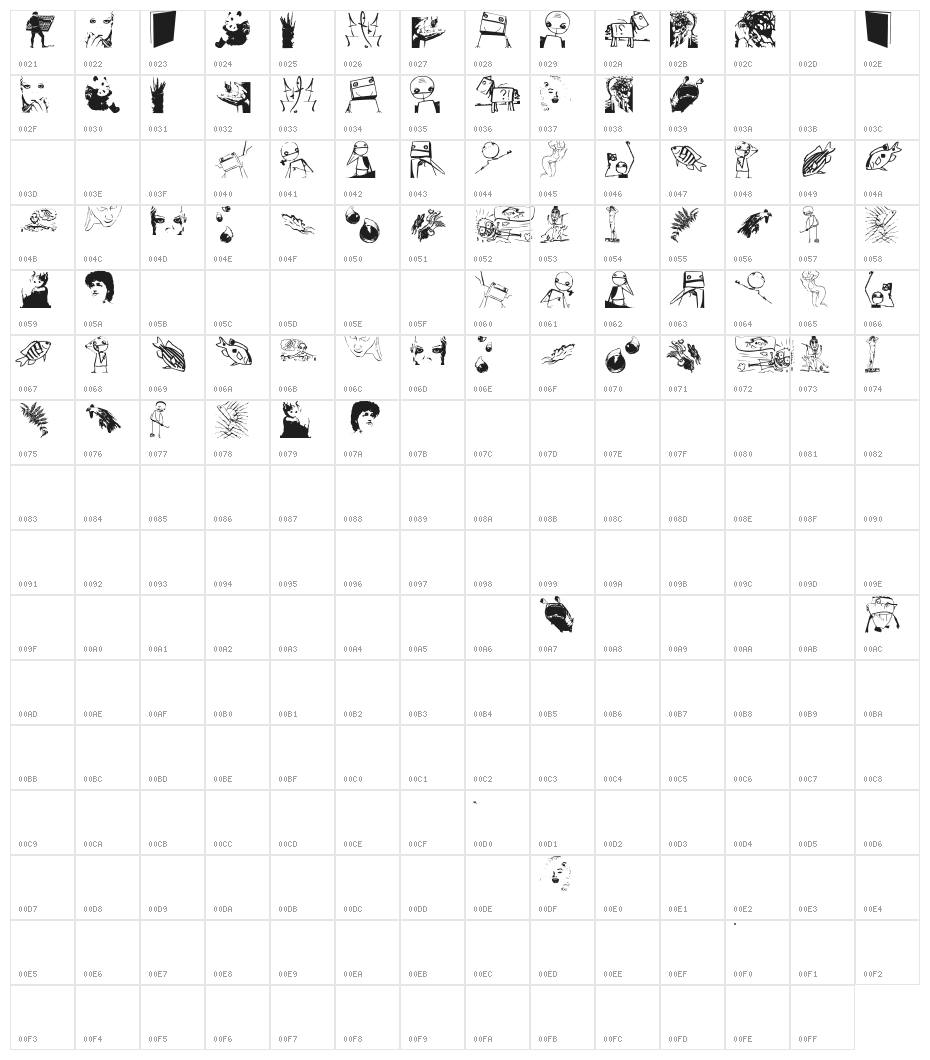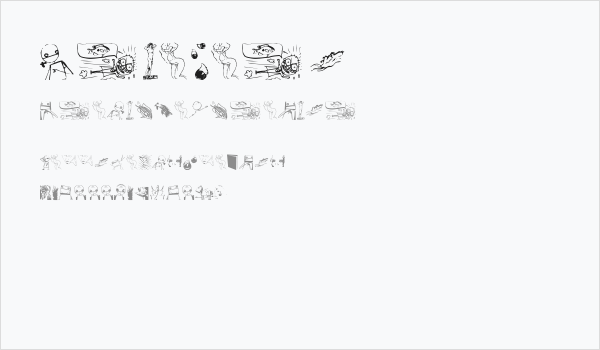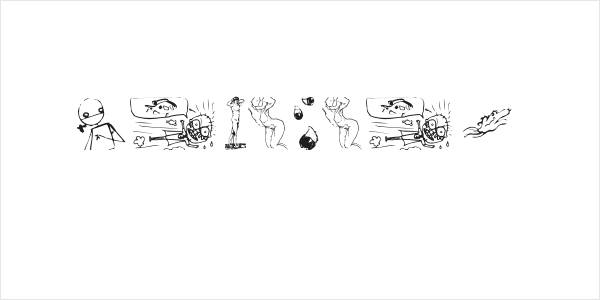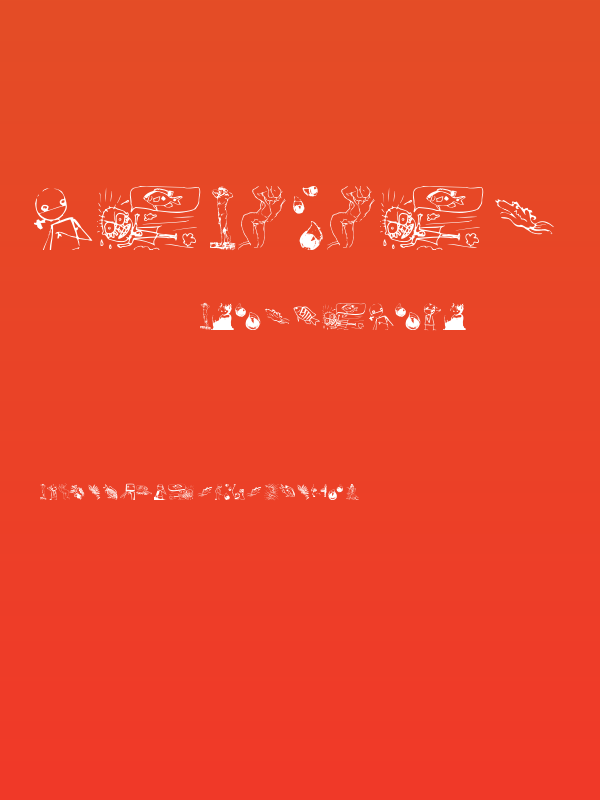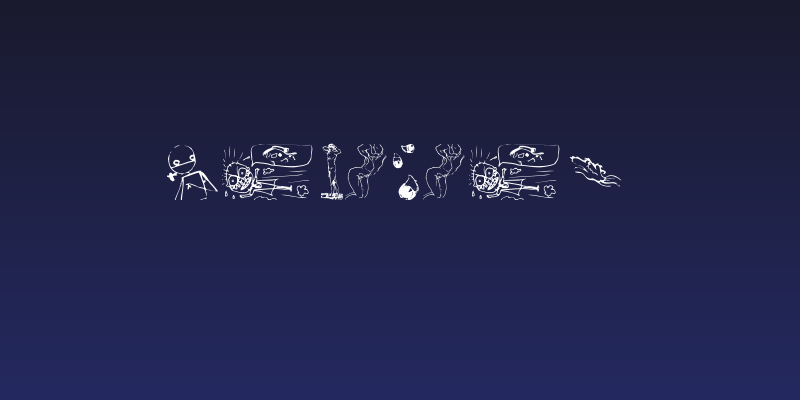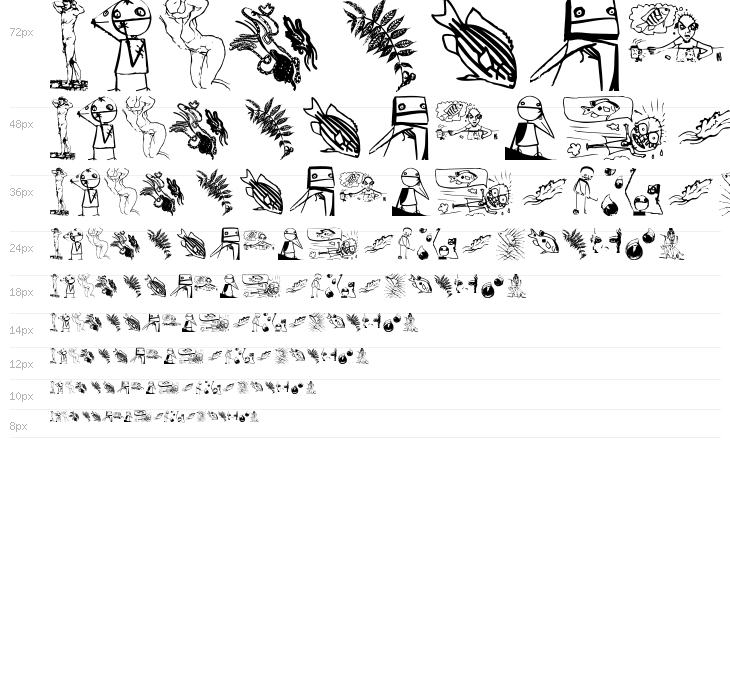
ArteNero Font
| Gesamtstil | Artistic, Illustrative |
| Anwendungsfall | Art projects, Illustrations |
| Vorgeschlagene Projekte | This set of illustrations could be used for creative projects such as graphic novels, art prints, or unique branding elements. |